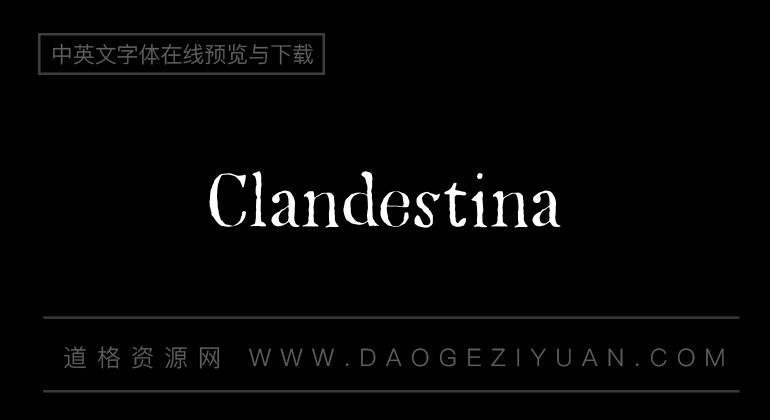
Clandestina
? Clandestina 字体是一款由西班牙设计师Lucas Le Bihan设计的开源字体,它的特点是可以模仿不同的文字风格,比如维拉语、西班牙语、葡萄牙语、英语等。它的字体风格可以提供几种不同的变体,以满足您的不同需求,比如:细体、粗体、斜体、线条等。Clandestina字体的字形清晰、细腻,可以为您的文字提供丰富的表达方式,是一款非常优秀的字体。
Clandestina是一款非常不错的手写艺术字体,具有很好的视觉感,适合于文化类的宣传设计、商业类品牌的广告和产品包装设计以及个性化文字排版等较多场景。
Clandestina字符映射图